Altdeutsche Schrift: Lesen, Lernen & Sütterlin verstehen
Die altdeutsche Schrift ist mehr als nur Tinte auf Papier; sie ist ein kulturelles Erbe, das uns direkt mit unseren Vorfahren verbindet. Wenn wir heute alte Dokumente, vergilbte Briefe oder Kirchenbücher aufschlagen, fühlen wir uns oft wie Archäologen, die eine längst vergangene Welt freilegen. Doch für viele bleiben diese Zeilen ein Rätsel. Die schwungvollen Bögen und spitzen Winkel wirken oft eher wie eine Zeichnung als wie lesbarer Text.
In diesem Artikel nehme ich Sie mit auf eine Reise durch die Geschichte der deutschen Schreibkultur. Wir schauen uns an, was es mit Sütterlin und Kurrent auf sich hat, und ich gebe Ihnen das Werkzeug an die Hand, um diese faszinierenden Zeugnisse der Geschichte selbst zu entschlüsseln. Egal, ob Sie Ahnenforschung betreiben oder einfach nur ein Tattoo in historischem Stil planen – das Verständnis für die alten Formen ist der Schlüssel.
Was ist altdeutsche Schrift eigentlich?
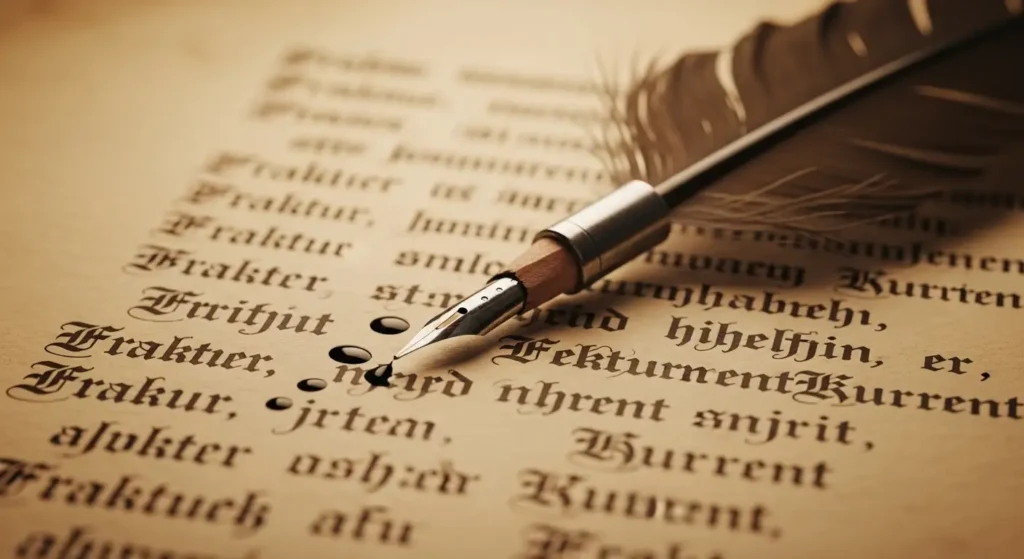
Wenn wir umgangssprachlich von “altdeutscher Schrift” sprechen, werfen wir oft verschiedene Schriftarten in einen Topf. Historisch betrachtet ist dieser Begriff ein Sammelbecken für diverse gebrochene Schriften und Schreibschriften, die im deutschsprachigen Raum vom 16. bis zur Mitte des 20. Jahrhunderts verwendet wurden.
Die Unterscheidung ist wichtig, um Dokumente zeitlich einordnen zu können. Grob lässt sich sagen: Was gedruckt wie “Schnörkel” aussieht, ist meist Fraktur. Was handgeschrieben schwer lesbar wirkt, ist in der Regel die deutsche Kurrentschrift oder ihre spätere, vereinfachte Form, die Sütterlinschrift.
Das Besondere an diesen Schriften ist der sogenannte “Duktus” – die Art und Weise, wie die Feder geführt wird. Während wir heute meist eine lateinische Ausgangsschrift nutzen, basieren die alten Stile auf abrupten Richtungswechseln, die den Buchstaben ihren charakteristischen, gebrochenen Look verleihen. Wer unseren Schriftgenerator nutzt, bekommt einen direkten visuellen Eindruck dieser Ästhetik.
Die Evolution: Von Kurrent bis Sütterlin
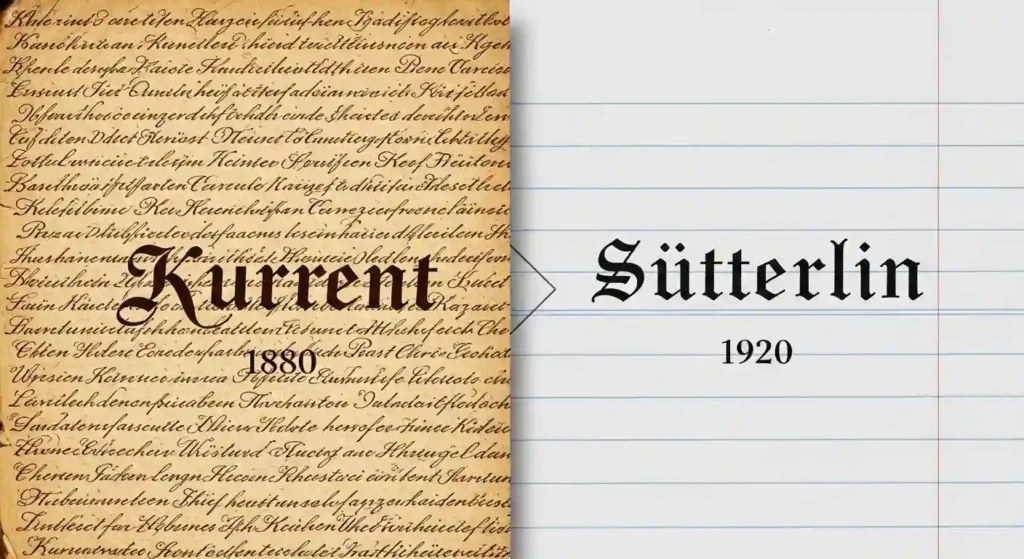
Um alte Texte wirklich zu verstehen, müssen wir die Evolution der Schriftzeichen nachvollziehen. Es war kein statisches System, sondern eine lebendige Entwicklung über Jahrhunderte hinweg.
Die deutsche Kurrentschrift
Die Kurrentschrift war über Jahrhunderte die Verkehrsschrift schlechthin. Sie etablierte sich im frühen 16. Jahrhundert und war bis 1914 die offizielle Amts- und Verkehrsschrift. Ihre Merkmale sind spitze Winkel (daher auch “Spitzschrift” genannt) und eine starke Rechtsneigung. Wenn Sie Briefe aus dem 18. oder 19. Jahrhundert finden, sind diese mit fast hundertprozentiger Wahrscheinlichkeit in Kurrent verfasst.
Die Sütterlinschrift (1911–1941)
Hier kommt oft Verwirrung auf. Ludwig Sütterlin, ein Grafiker aus Berlin, wurde beauftragt, eine einfachere Schrift für Schulanfänger zu entwickeln. Die alte Kurrent war mit ihren feinen Haarstrichen und wechselndem Druck für Kinderhände mit Stahlfedern schwer zu meistern. Sütterlin vereinfachte die Formen: Die Buchstaben wurden aufrechter, die Linien gleichmäßiger, und die Verhältnisse von Ober-, Mittel- und Unterlängen wurden standardisiert (1:1:1).
Sütterlin ist also eigentlich eine “Schulausgangsschrift”. Sie wurde 1915 in Preußen eingeführt und prägte eine ganze Generation. Viele Dokumente aus den 1920er und 30er Jahren sind in Sütterlin verfasst. Oft wird der Begriff altdeutsche Schrift heute fälschlicherweise synonym nur für Sütterlin verwendet, obwohl es nur ein kurzes Kapitel in der langen Geschichte ist.
Praktische Anwendung: Warum wir das heute noch brauchen
Man könnte meinen, das alles sei Schnee von gestern. Doch das Interesse wächst stetig. Ahnenforschung ist zu einem wahren Volkssport geworden. Wer wissen will, wer seine Vorfahren waren, kommt an den Kirchenbüchern und Standesamtsunterlagen nicht vorbei. Und diese sind bis 1941 fast ausschließlich in deutschen Schreibschriften geführt.
- Familiengeschichte: Das Tagebuch des Urgroßvaters oder Feldpostbriefe aus dem Ersten Weltkrieg erzählen persönliche Geschichten, die in keinem Geschichtsbuch stehen.
- Design und Kunst: Viele Künstler nutzen die Ästhetik für Logos oder Tattoos. Ein Tattoo Schrift Generator zeigt, wie beliebt diese Stile heute wieder sind.
- Historische Forschung: Ohne Paläografie (die Lehre von alten Schriften) wäre unsere Geschichtsschreibung lückenhaft.
Tipps und Tricks zum Lesen lernen
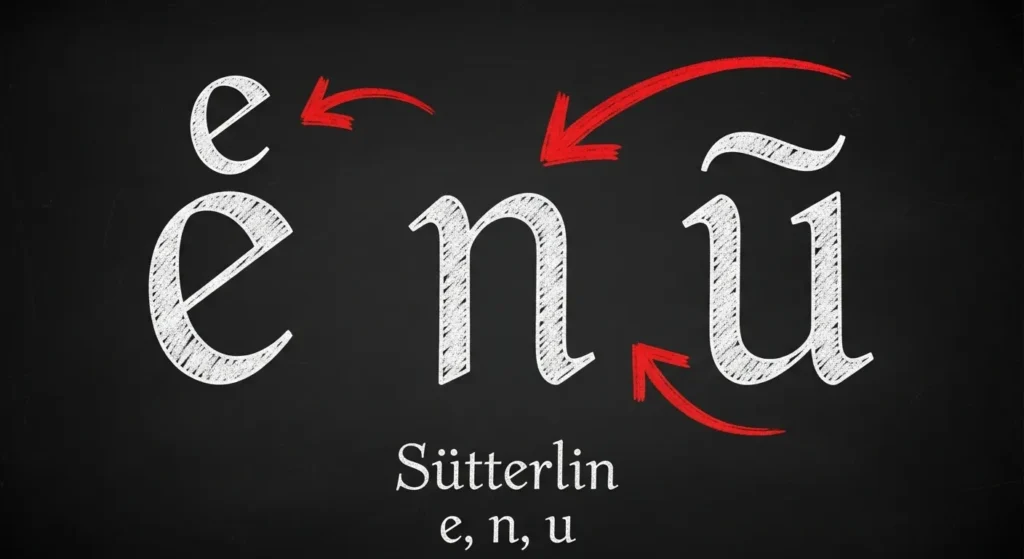
Aller Anfang ist schwer, aber mit ein paar Kniffen werden Sie schnell Fortschritte machen. Das menschliche Gehirn ist wunderbar darin, Muster zu erkennen.
1. Vergleichen Sie Buchstaben
Suchen Sie sich ein Wort im Text, das Sie sicher lesen können (oft Namen oder Orte). Vergleichen Sie die Buchstaben dieses Wortes mit unbekannten Wörtern. Das ist wie ein Puzzle, bei dem sich das Bild langsam zusammensetzt.
2. Achten Sie auf das “e”, “n” und “u”
In der Kurrentschrift sehen “n” und “u” fast identisch aus. Der einzige Unterschied ist ein kleiner Bogen (der u-Bogen) über dem “u”. Das “e” hingegen sieht oft aus wie ein modernes “n”. Das führt oft zu Verwirrung. Merken Sie sich: Zwei vertikale Striche eng beisammen sind ein “e”, weiter auseinander ein “n” oder “u”.
3. Das lange “s”
Ein klassischer Stolperstein. Es gibt in der alten Schrift zwei Arten von “s”. Das runde “s” steht am Wortende, das lange “s” (das aussieht wie ein “f” ohne den kompletten Querstrich) steht am Wortanfang und in der Wortmitte. Ein hilfreicher externer Ressourcen-Tipp ist oft das Göttinger Digitalisierungszentrum, wo man viele Originaldokumente zum Üben findet.
Häufig gestellte Fragen (FAQ)
Wurde Sütterlin von den Nazis verboten?
Ja, tatsächlich. 1941 erließ die NSDAP den sogenannten Normalschrifterlass. Ironischerweise bezeichneten sie die gebrochenen Schriften (Fraktur und Sütterlin) plötzlich als “Schwabacher Judenlettern” und verboten sie. Seitdem wurde an deutschen Schulen die lateinische Ausgangsschrift gelehrt.
Wie schwer ist es, altdeutsche Schrift zu lernen?
Es ist einfacher, als es aussieht. Die altdeutsche Schrift folgt logischen Regeln. Mit etwa einer Woche täglicher Übung (15 Minuten reichen oft) können die meisten Menschen bereits einfache Texte flüssig lesen. Das Schreiben erfordert etwas mehr motorische Übung.
Gibt es Apps zum Übersetzen?
Es gibt mittlerweile KI-gestützte Apps, die versuchen, Handschriften zu transkribieren. Die Ergebnisse sind jedoch oft durchwachsen, besonders bei individuellen Handschriften. Das menschliche Auge und Kontextwissen sind hier der Technik noch oft überlegen.
Fazit: Ein lohnendes Hobby
Die Beschäftigung mit alten Schriften ist eine Bereicherung. Sie öffnet Türen zu unserer eigenen Geschichte, die sonst verschlossen blieben. Es ist ein Handwerk, das Geduld erfordert, aber mit tiefen Einblicken belohnt wird.